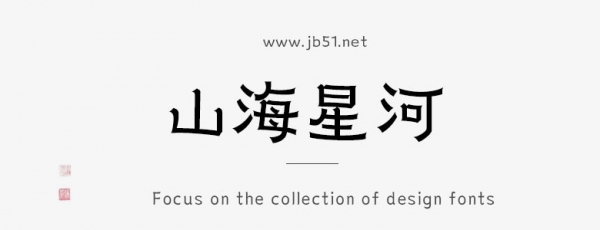
山海星河家族是由山海字庫出品的字體,這款字體擁有六款字重,具有很好的視覺感,適合應(yīng)用于藝術(shù)設(shè)計、平面宣傳設(shè)計、網(wǎng)頁設(shè)計,書法字帖等領(lǐng)域,需要的朋友可以前來本站下載。
山海星河,由山海字體社出品。本字體為簡繁字庫,采用Adobe-GB1-5編碼,包含常用簡體(GB2312-80)6763個,繁體(GBK)2406個,共計9169個漢字;以及ASCIl常用西文200+。6個字重-45-Light 55-Normal65-Regular75-Medium 85-Bold95-Heav
山海星河家族(45W/55W/65W/75W/85W/95W)